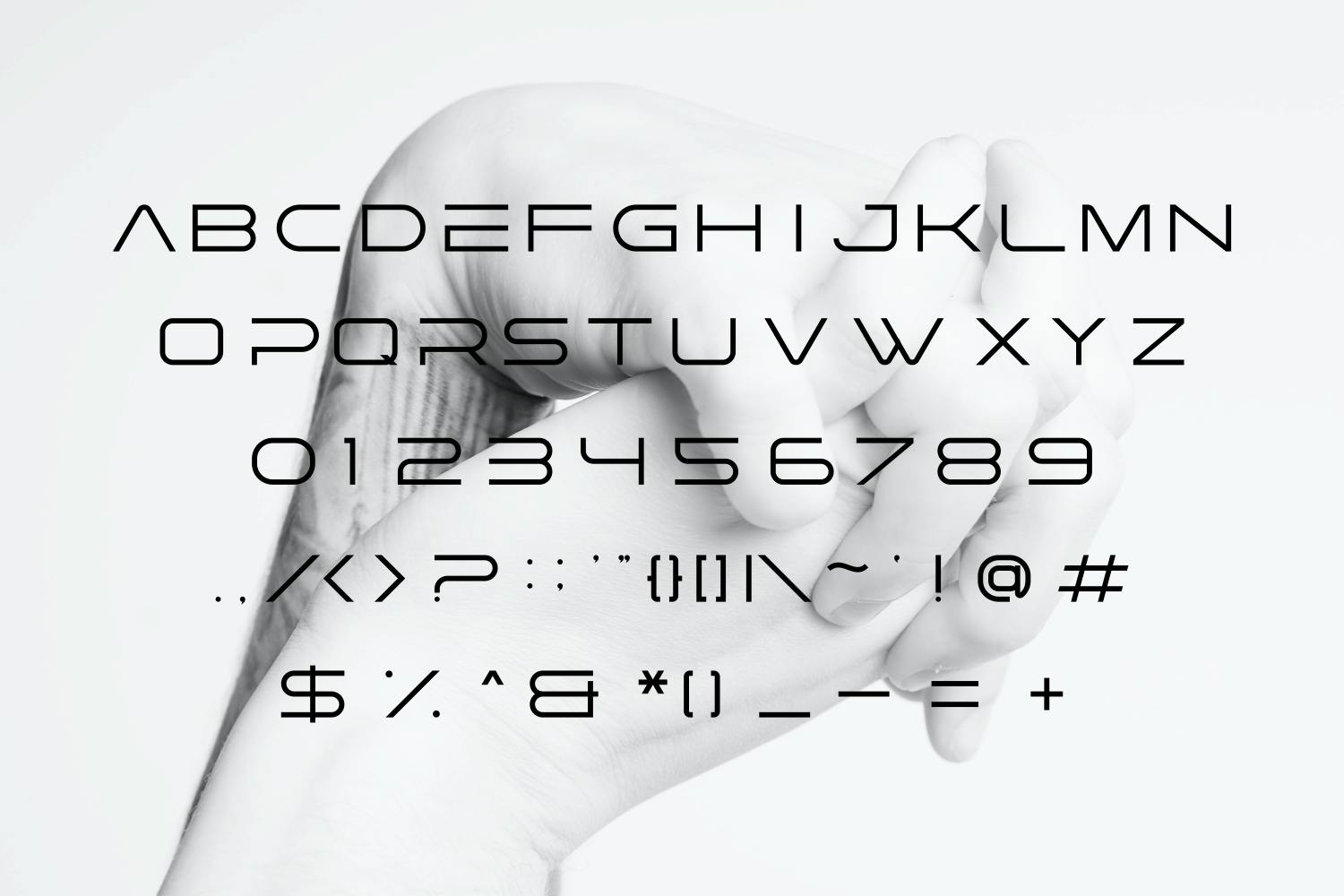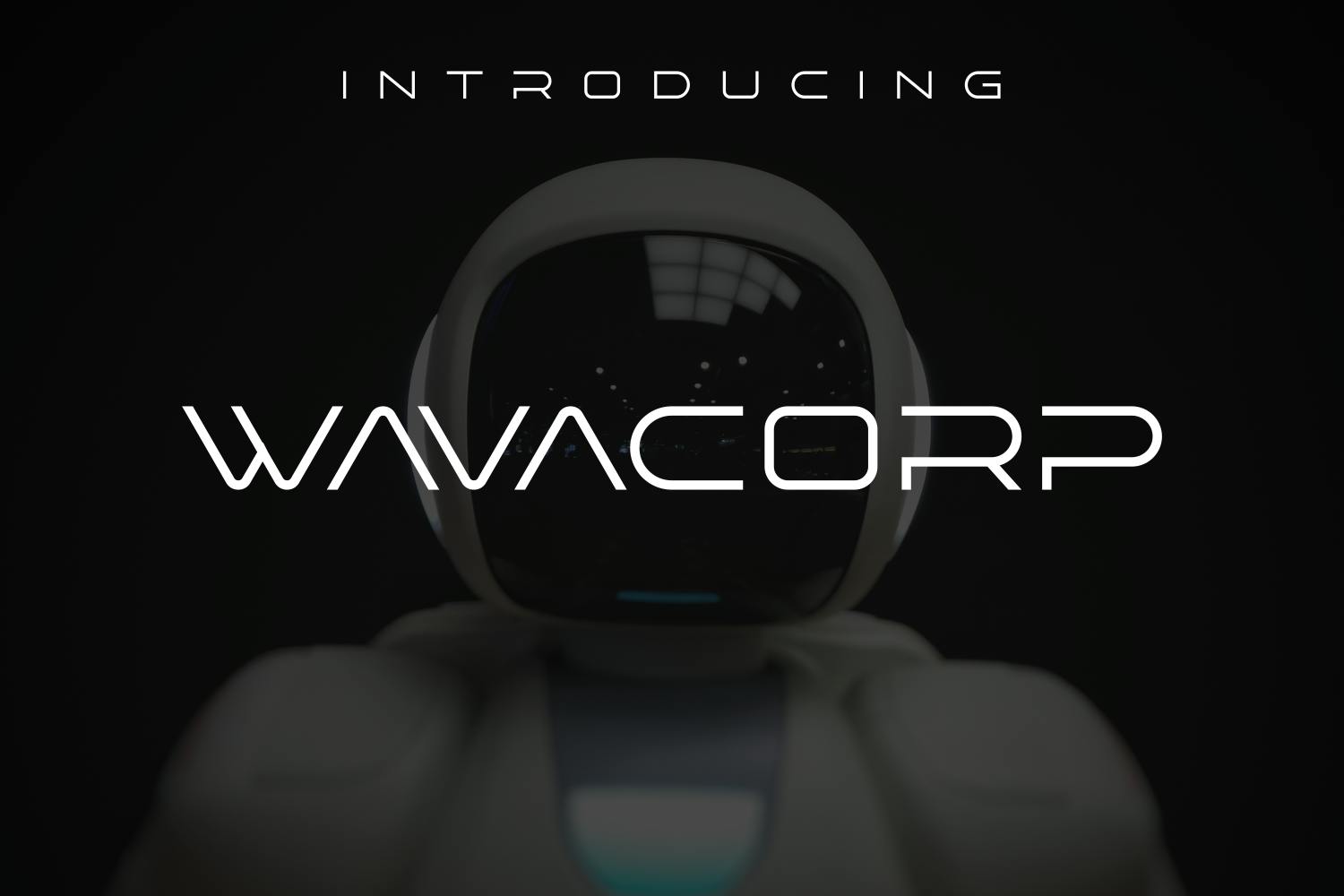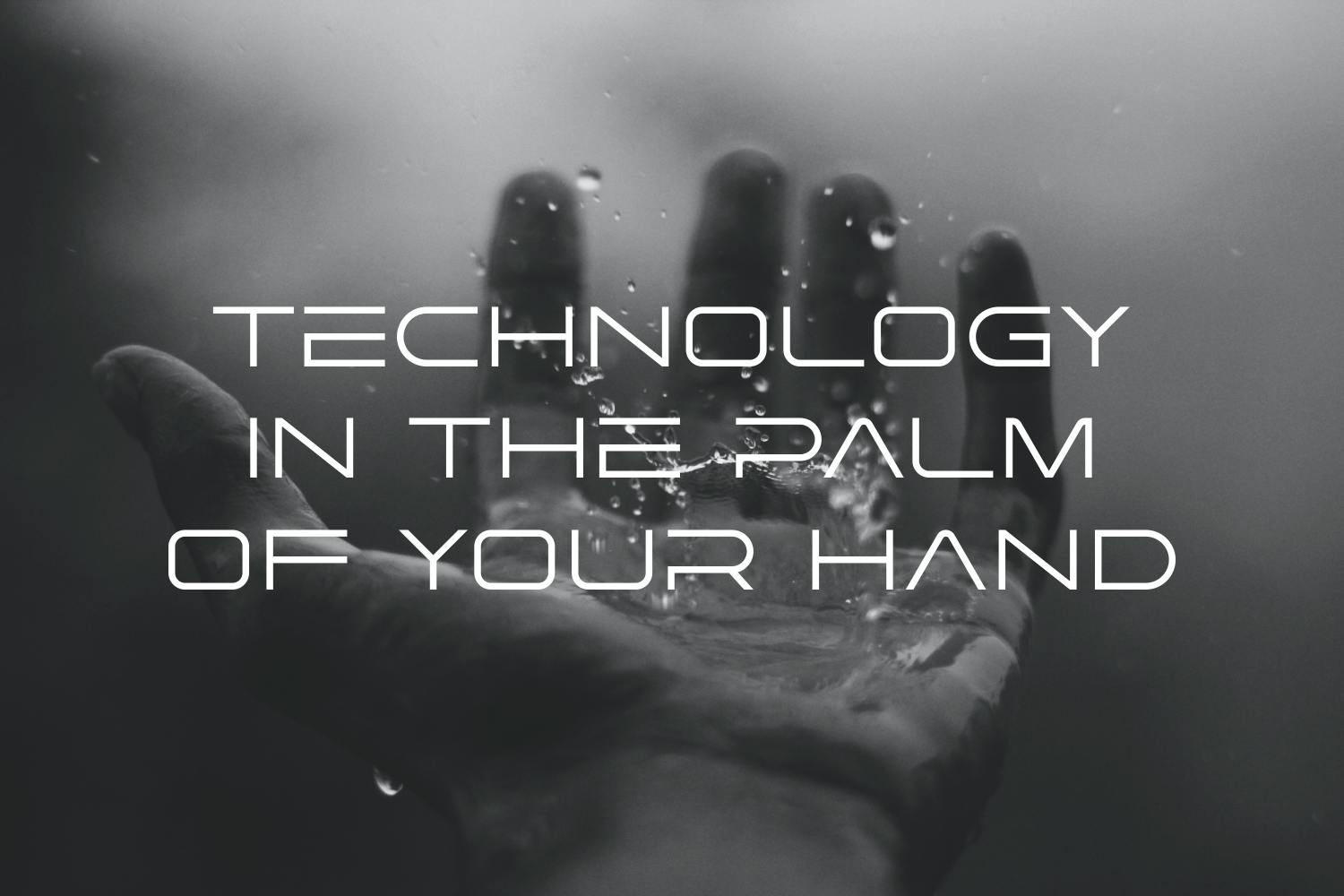
دانلود فونت مدرن Wavacorp با طراحی منحصر به فرد
Wavacorp modern font
فونت Wavacorp، انتخابی مناسب برای پروژه‌های شما.
Wavacorp یک فونت مدرن، عریض و گرد است که به عنوان یک راه‌حل برندینگ و ویرایشی طراحی شده است. این فونت به گونه‌ای طراحی شده که قابلیت استفاده در پروژه‌ها و رسانه‌های مختلف را دارد و به عنوان یک گزینه انعطاف‌پذیر و چندمنظوره شناخته می‌شود.
• طراحی مدرن و منحصر به فرد
• مناسب برای طراحی لوگو و برندینگ
• قابل استفاده در پروژه‌های چاپ و دیجیتال
• انعطاف‌پذیری بالا در استفاده‌های مختلف